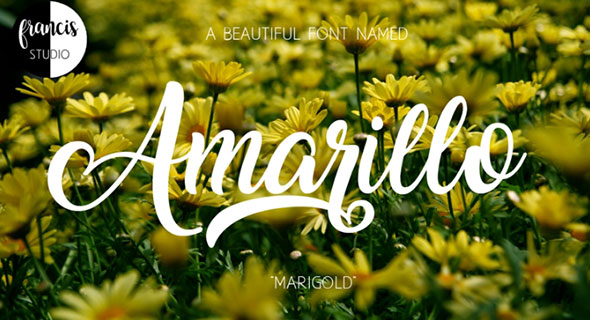
【デザイナー必見!】これは使える! スクリプトフォント20選!!
スクリプトフォントや筆記体式のフォントは、印刷媒体とデジタル媒体双方において大変利用価値の高いフリーイラストです。もしあなたが手書きタイプのフォントがお好きでしたら、この記事はあなたのためにあると言っても過言ではありません!ここでは厳選した20種類のスクリプトフォントを紹介します。あなたの今のお仕事やこれからのプロジェクトに是非ともお役立てください。
これらのフォントには、プロフェッショナルな見映えのディテールと手書きのタッチが効いており、フェミニンにもエレガントにもプロジェクトを彩ってくれるでしょう。また、大文字と小文字を交互に使用することも一般的であること、そうすることでユニークな見映えになることにもお気づき頂けるでしょうしょう。
これらの印象的なフォントはあなたのデザインをプロ仕様とするのに役立つでしょう。是非これらのスクリプトフォントを手元にダウンロードし、結婚式招待状やTシャツのデザイン、カード、ポスター、ブランディング、広告、Instagramへの投稿など、複数のシーンにおいて活用してください。まずは全て参照してみて、あなたの好みのものを探しましょう。楽しまないと損ですよ!
Shorelines(ショアライン)
Shorelinesはあなたのプロジェクトで活用できる美しいスクリプトフォント。小文字と大文字を組み合わせた美しい筆記体調の見映えです。
Hello-Stockholm(ハロー・ストックホルム)
モダンなタッチの手書きタイプの見た目のフォントです。ユニークかつ印象的なプロスタイルのデザインフォントです。
Noelan(ノエラン)
Noelanは、現代的デザインと国際的な雰囲気を持つ美しいなスクリプトフォント。是非ダウンロードしてデジタル媒体にも印刷媒体にもご活用ください。
オールド・グロウス
Old Growthは自然に喚起されたイメージの美しい筆記体フォント。様々なタイプの文字が規則性のない筆先や交互に使用されていることがユニークなデザインを生んでいます。
ワイルド・ユース
ワイルド・ユースはハンドスケッチのデザインが素晴らしいスクリプトフォントです。無料でダウンロード可能。商用にも個人用にも活用してください。
Caleb(カレブ)
Calebは素敵な筆記体調のフォントで、無料でダウンロードしてあらゆるプロジェクトで活用可能です。個人でも商業用にも使うことができる便利なフォントです。
Bartolomew(バルトロメ)
Bartolomewはヴィンテージ風の独特の筆記体です。あなたは無料でこのアイテムをダウンロードして、個人的および商業的目的で使用することができます。
Humble Rough(ハンブルラフ)
Humble Roughtは美しいヴィンテージスタイルの手書きフォントです。ダウンロードして、結婚式の招待状やグリーティングカード、ブランディング、ポスターなど幅広く活用してください。
LSTK Bembo
LSTK Bemboはすばらしい筆記体調のフォントで、無料でダウンロード可能。まずはデザインを見てみて、あなたのプロジェクトでぜひ活用してください。
ブルックス
BRUXは創造的なデザインの光る素晴らしいブラシ調のフォントです。ダウンロードして印刷媒体にもデジタル媒体にも活用ください。
Bizon
Parabelo(パラベロ)
Parabelo(パラベロ)はMarcelo Reis Melo作のブラシスタイルの美しいスクリプトフォントです。印刷媒体にもデジタル媒体にもダウンロードして活用してください。
Reis Handmade(レイスハンドメイド)
Reis Handmade(レイスハンドメイド)。こちらもMarcelo Reis Meloによってデザインされた素敵な無料スクリプトフォントです。現在お仕事や今後のお仕事のため、是非ダウンロードしておいてください。
スムージーショップ
Smoothie Shoppeは、印刷媒体にもデジタル媒体にも使用できるユニークなスクリプトフォントです。あなたのプロジェクトでそれを使用できるか是非確認してください。
Amarillo(アマリロ)
アマリロは、個人利用用の美しい筆記体調の無料フォントです。この洗練されたフォントをダウンロードし、今後のプロジェクトでご活用ください。
ミルクシェーク
ミルクシェークは印象的なデザインが素敵なスクリプトフォントです。見出しにも背景にも最適ですよ。
Ruffle Beauty(フリル・ビューティー)
Ruffle Beautyは、ユニークなスクリプトフォントです。あなたは個人用にも商業用にも無料で使うことができます。
Sophia(ソフィア)
ソフィアは、ブラシ調の手描きのフォントです。あなたのスタイルに合っているかどうか是非確認して、楽しんでください!
King Basil(キングバジル)
King Basilはユニークなデザインの印象的なスクリプトフォントです。ダウンロードして印刷媒体にもデジタル媒体にも活用してください。
バッファロー
Buffaloは美しく幻想的なデザインのスクリプトフォントです。個人利用も商用にも無料で利用可能です。